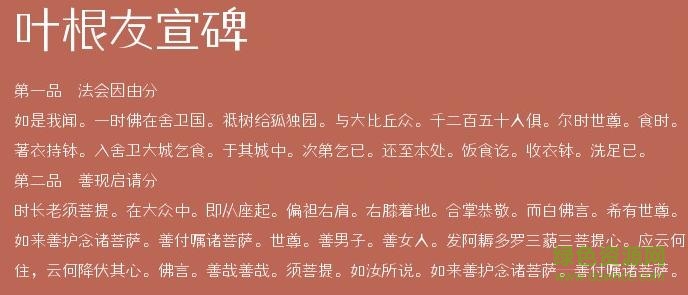
葉根友宣碑
葉根友宣碑字體是一款葉根友出品的簡體字體,字體大氣、字形優(yōu)雅,適用于文章標題、出版作品等等,書寫有力自帶碑體之勁道。大家可以來綠色資源網下載葉根友字體全集!
葉根友宣碑字體
葉根友宣碑字體大氣而不失遒勁古刻的字體,看似雜亂卻不失基本工整,非常的文雅好看,是漢字里面比較大方得體的了。